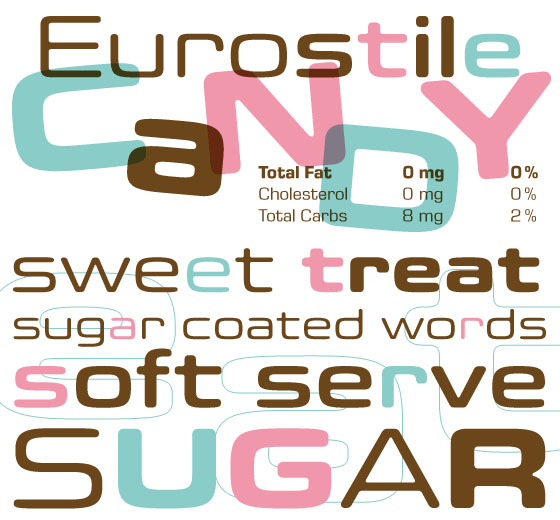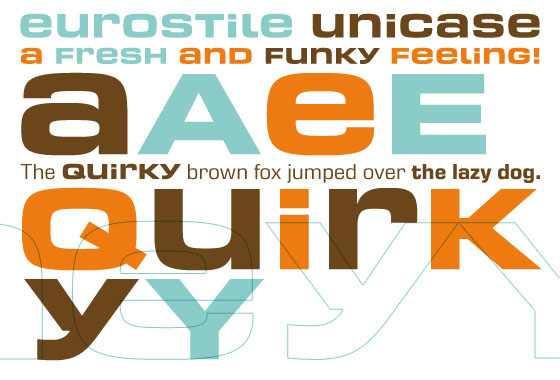
Eurostile Candy & Eurostile Unicase (Linotype)
Eurostile® Candy und Eurostile Unicase sind die sympathischen Begleiter der neuen Eurostile-Schriftfamilie. Beide werden durch die Idee der Eurostile inspiriert, wandeln diese jedoch in eine Headline-Form ab. Bei Eurostile Candy wurden die Ecken und Anschlusselemente abgerundet, was dem Schriftbild ein freundlicheres, weicheres Aussehen verleiht. Aber auch die Grundstrukturen vieler Buchstaben wurden verändert. Zusätzliche Linien wurden entfernt (z.B. bei a, s und t) und Buchstaben wie n oder r wurden vereinfacht. Bei der Eurostile Unicase wurden die Ober- und Unterlängen durch Alternativzeichen ersetzt, die alle die gleiche Höhe haben. Dies ergibt einen einzigartigen Effekt, als würde man nur Großbuchstaben verwenden, wie bei einer Unzialschrift. Unübliche Figuren verleihen dem Text ein frisches, unkonventionelles Aussehen. Probieren Sie die beiden Extraschriften für Überschriften und Titel aus und setzen Sie dann Ihren Text in Eurostile Next!
Ein paar Jahre zu spät oder? Unicase ist schon ein
ganz alter Hut und die Rounded-Phase ist eigentlich
auch schon vorbei ...
Knuffig ja. Inzwischen wäre ja eigenltich eher eine Eurostile mit halbabgerundeten Balken und Swash-Descenders fällig :lol:
komisch, nicht wahr? Ich hatte es eben im Emailpostfach. Mein erster Gedanke war: ach, jetzt versuchen sie es auch. Dann sah ich, dass die Schrift gar nicht schlecht ist, aber der Absender nicht unbedingt das Image von Innovation transportiert. Wäre diese Schrift bei einer kleinen Foundry oder beim Fontshop rausgekommen, wäre mein erster Eindruck sicher anders gewesen. Aber die hätten die Eurosweet auch sicher anders präsentiert.
Mit Linotype verbinde ich hochwertige Satzschriften, keine Trendgeschichten.
"Mit Linotype verbinde ich hochwertige Satzschriften, keine Trendgeschichten."
Genau das Problem habe ich immer wenn ich deren gedruckten Newsletter bekomme. Das soll so trendig wirken und ist doch irgendwie so altmodisch :?
Mehr Eurostile... muss ich nicht haben. Aber warum nicht.
"Mit Linotype verbinde ich hochwertige Satzschriften, keine Trendgeschichten."
Genau das Problem habe ich immer wenn ich deren gedruckten Newsletter bekomme. Das soll so trendig wirken und ist doch irgendwie so altmodisch :?
nicht nur die newsletter, auch die restlichen drucksachen versuchen immer trendig
zu wirken und sehen dadurch leider sehr altbacken aus. zu der schrift sage ich mal nix. :neenee: